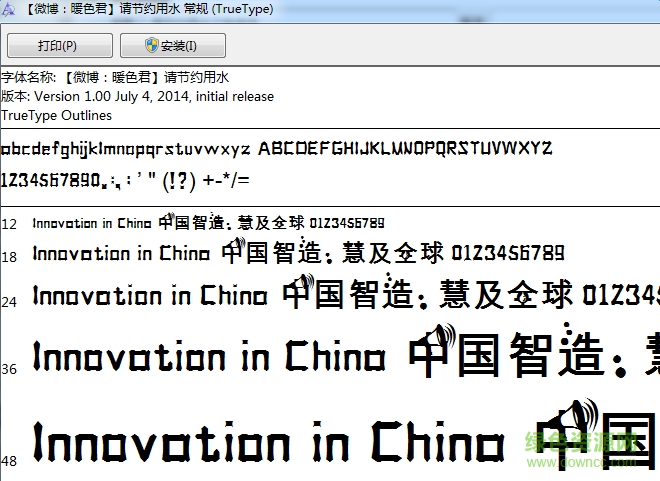
請(qǐng)節(jié)約用水字體是一款超好用的個(gè)性中文字體,該字體可以廣泛應(yīng)用于廣告設(shè)計(jì)、宣傳海報(bào)、ppt、影視制作以及任何使用文字的領(lǐng)域,有需要的朋友可以免費(fèi)下載收藏。
請(qǐng)節(jié)約用水字體是一款極具個(gè)性的字體,該字體十分飄逸,彰顯了自己的個(gè)性,有喜歡的朋友可以來(lái)綠色資源網(wǎng)下載使用!